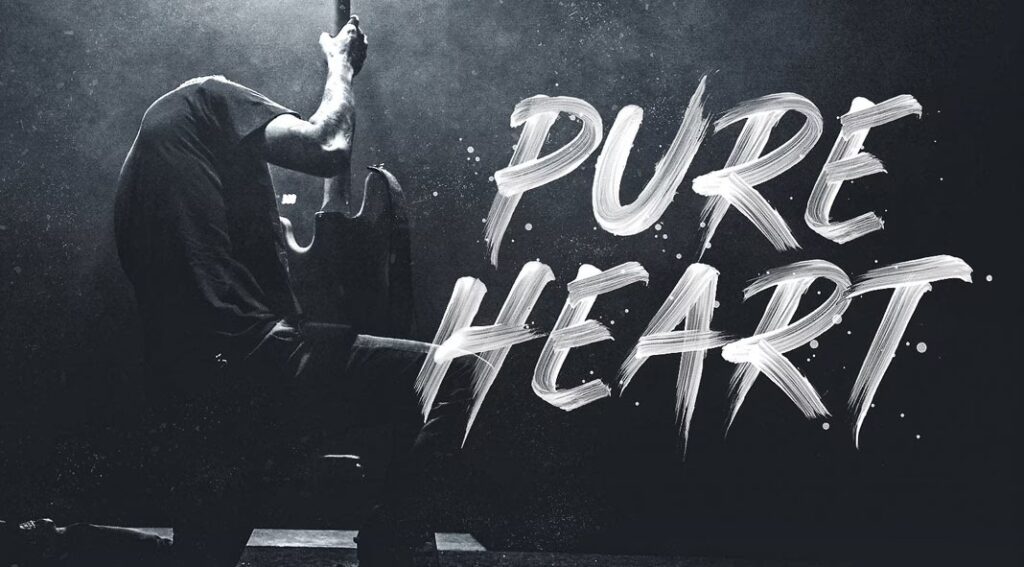
I en verden af grafisk design og typografi er valget af den rette skrifttype afgørende for et projekts succes. Pensel- eller 'brush'-skrifttyper er blevet utroligt populære for deres organiske, håndskrevne udseende, der kan tilføre personlighed og dynamik til ethvert design. En sådan skrifttype, der ofte fanger designeres opmærksomhed, er 'Brusher'. Men når man arbejder med designs, der skal bruges professionelt eller sælges, opstår et vigtigt spørgsmål: Er Brusher skrifttypen fri til kommerciel brug?
Hvad Må Du Ikke med Brusher Licensen?
Lige så vigtigt som at vide, hvad du må, er det at kende begrænsningerne. Licensen for Brusher indeholder klare forbud:
- Du må ikke videresælge, underlicensere eller redistribuere selve skrifttype-filerne. Dette gælder, selvom du ikke tager penge for det. Du må altså ikke lægge filen op på din egen hjemmeside til download, sende den direkte til en ven, eller inkludere den som en separat fil i et produkt.
- Skrifttype-filerne må ikke sælges 'på egen hånd' eller som 'en separat vedhæftning' fra dit arbejde. Dette understreger, at licensen dækker *brugen* af fonten i dine designs, men ikke ejerskabet eller distributionen af fontfilen i sig selv.
- Hvis du ønsker at promovere Brusher på din egen hjemmeside eller blog, skal du linke tilbage til den originale ressource-side (f.eks. på GraphicBurger), hvor brugerne kan finde den officielle download, og ikke linke direkte til download-filen.